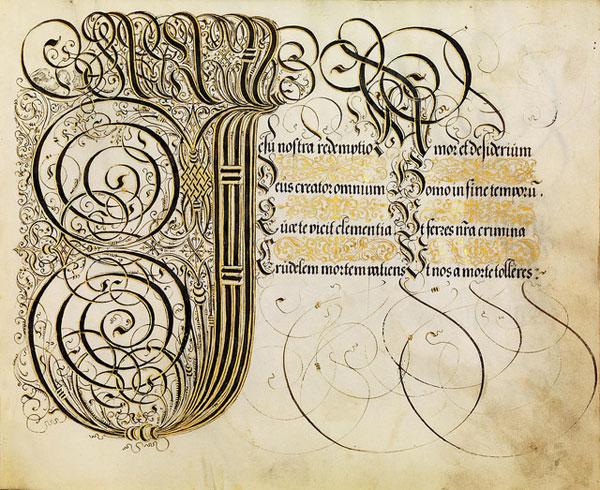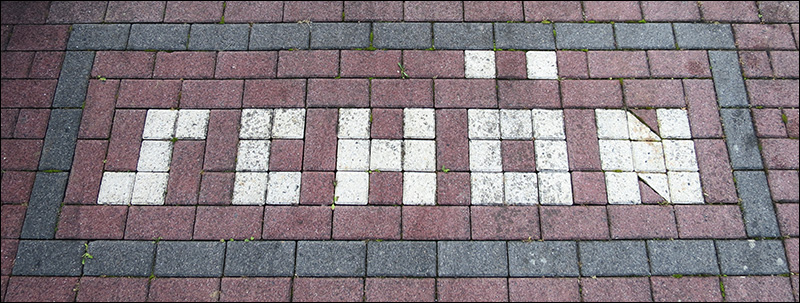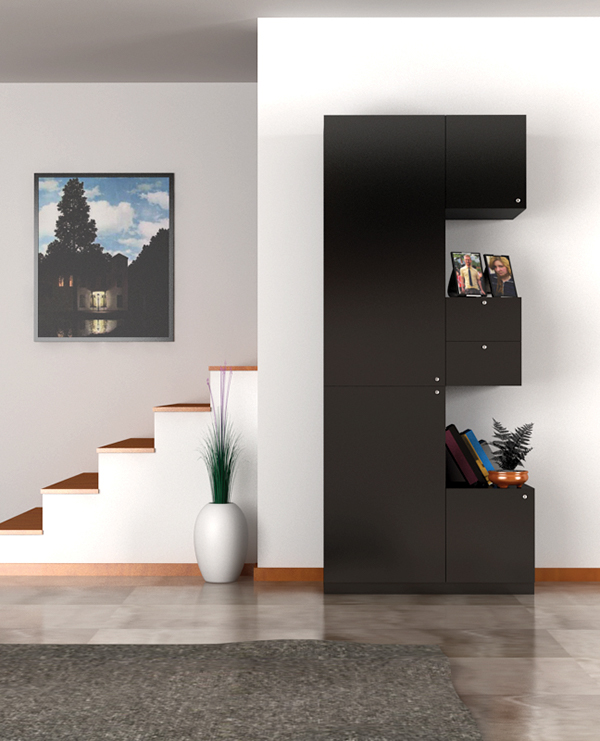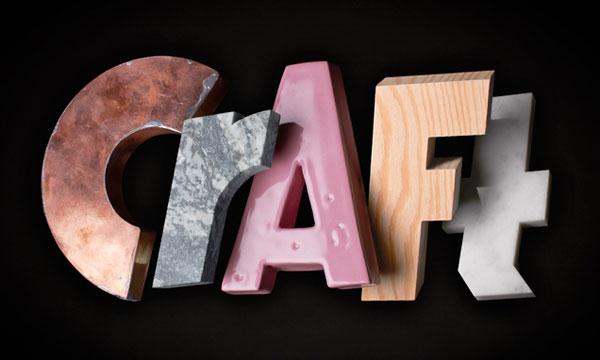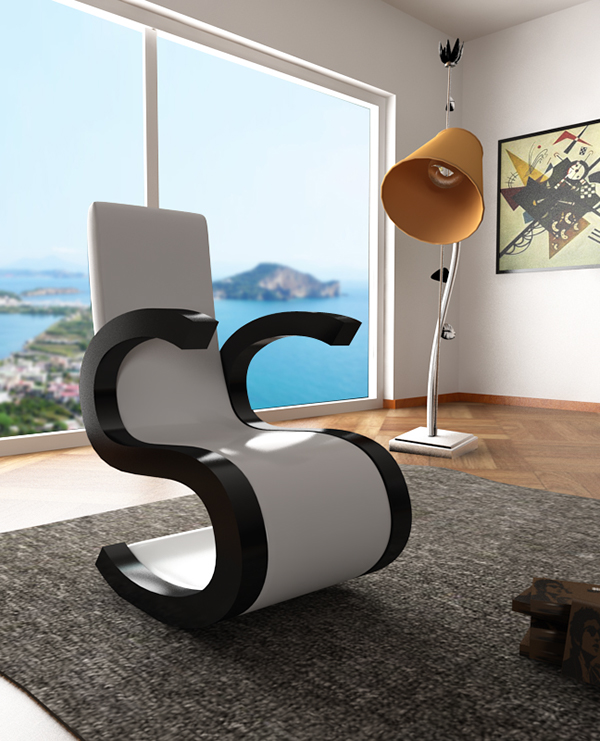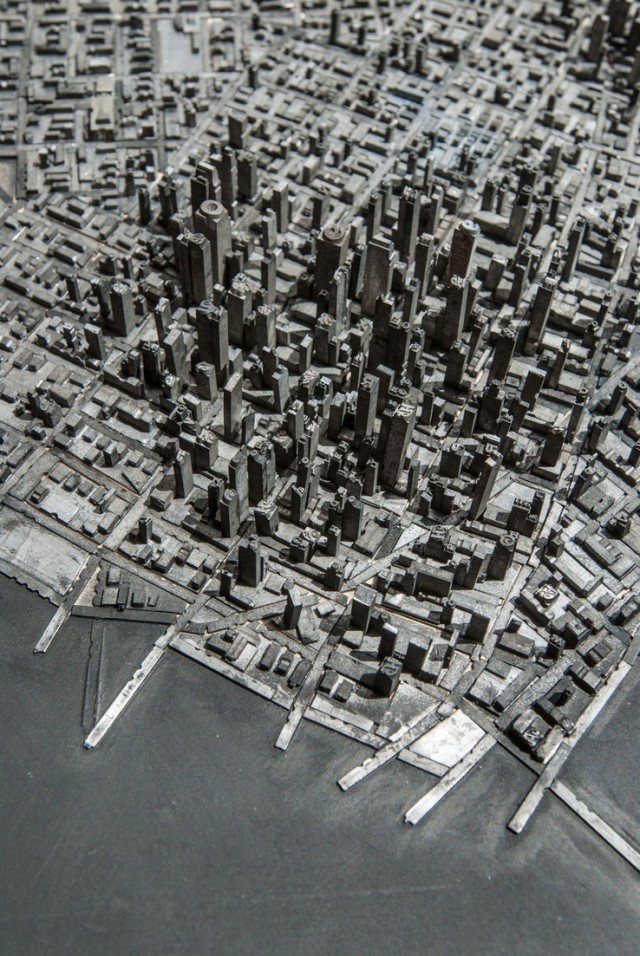
Das musst du natürlich selbst entscheiden, Peter. In den kurzen Mengentexten komme ich mit dem t auch ganz gut klar, nur in der extra-fetten Version, in der die Artennamen gesetzt sind, will es mir so gar nicht wie ein Buchstabe erscheinen, besonders bei der Palmaube. :-?
geht mir genau so. ich fand es erst auch irgendwie bedauerlich, dass diese taubenart flächendeckend vom baum genommen wurde. und dann bezweifelte ich, dass im französischen departement aube (mit troyes als hauptstadt) palmen wachsen, auf denen tauben … und warum sollten sie auch … hä? verwirrlich. und wirklich ein totschläger, dieses «t».
Hatten wir das nicht schon mal? Ich kann mich an das O aus dem Kopenhagener Rundetaarn erinnern, das ich damals gepostet hab …
LOL, genau das Foto vom O benutze ich immer noch in meiner Vorlesung über DNA-Replikation! :hammer:
Das freut mich  :biglove:
:shock:
Na wenigstens war hier nicht die Frage: "Wie heißen all die verwendeten Schriftarten (bitte den Logos genau zugewiesen) Und bitte schnell!!!"
Na dann fang mal an mit Nachbauen der kompletten Schriften  :hammer:
aus cat- wird dann aber cheetahfonts.
Wegen der Geschwindigkeit? Dann könnte er aber auch zum Hobie Cat werden. ;-)
hobie cat? ich drudle googelnd, gurgelnd … wasser, wind, wellen und so?
Ne, dann lieber nicht,. ich werd einfach viel zu leicht seekrank. Schon auf den St.Pauli Landungsbrücken wird mir übel :-(
Ich musste vor einiger Zeit mit den HADAG-Hafenfähren nach Finkenwerder, weil ich Freunbde für die Heinfahrt treffen wollte., Als ich dort ankam fragten die "Wie siehst du den aus, bist du Krank?" so bleich war mein  Gesicht.
Aber ich glaube auch nicht, dass es sich lohnt. die nachzubauen, schließlich sinds ja alles computergenerierete Bildchen, daher dürften das nahezu alle hingezuppelte Computerschriften sein.
Oh nee, dann musst Du natürlich nicht übers Wasser flitzen. Wobei Du das Flitzen am nächsten Schietwettertag auch gerne in Pfützenhopsen umtauschen kannst.  :trost:
Eine quasi unendlich Anzahl[:] 901
Also wenn Journalisten solch einen Unsinn schreiben – und sie tun das sehr gern – kräuseln sich mir schon die Fußnägel. :nana: Dass ich das in einem Forum von i.a.R. überduchschnittlich pedantischen Menschen nun auch lesen muss, hätte ich eigentlich nicht gedacht. :shock:
SCNR :aschehaupt:
Unsinn [...] von i.a.R. überduchschnittlich pedantischen Menschen nun auch lesen muss, hätte ich eigentlich nicht gedacht. :shock::aschehaupt:
Das ist doch kein Unsinn, nur ein rhetorisches Stilmittel jemandes, der so weit weg von mathematischer Präzision lebt wie es nur irgendwie geht.